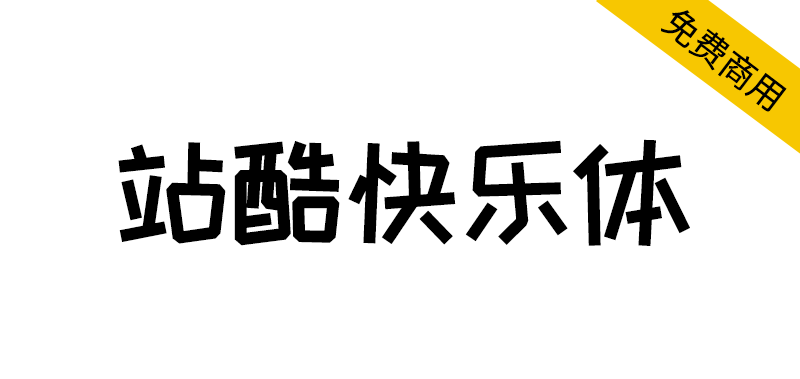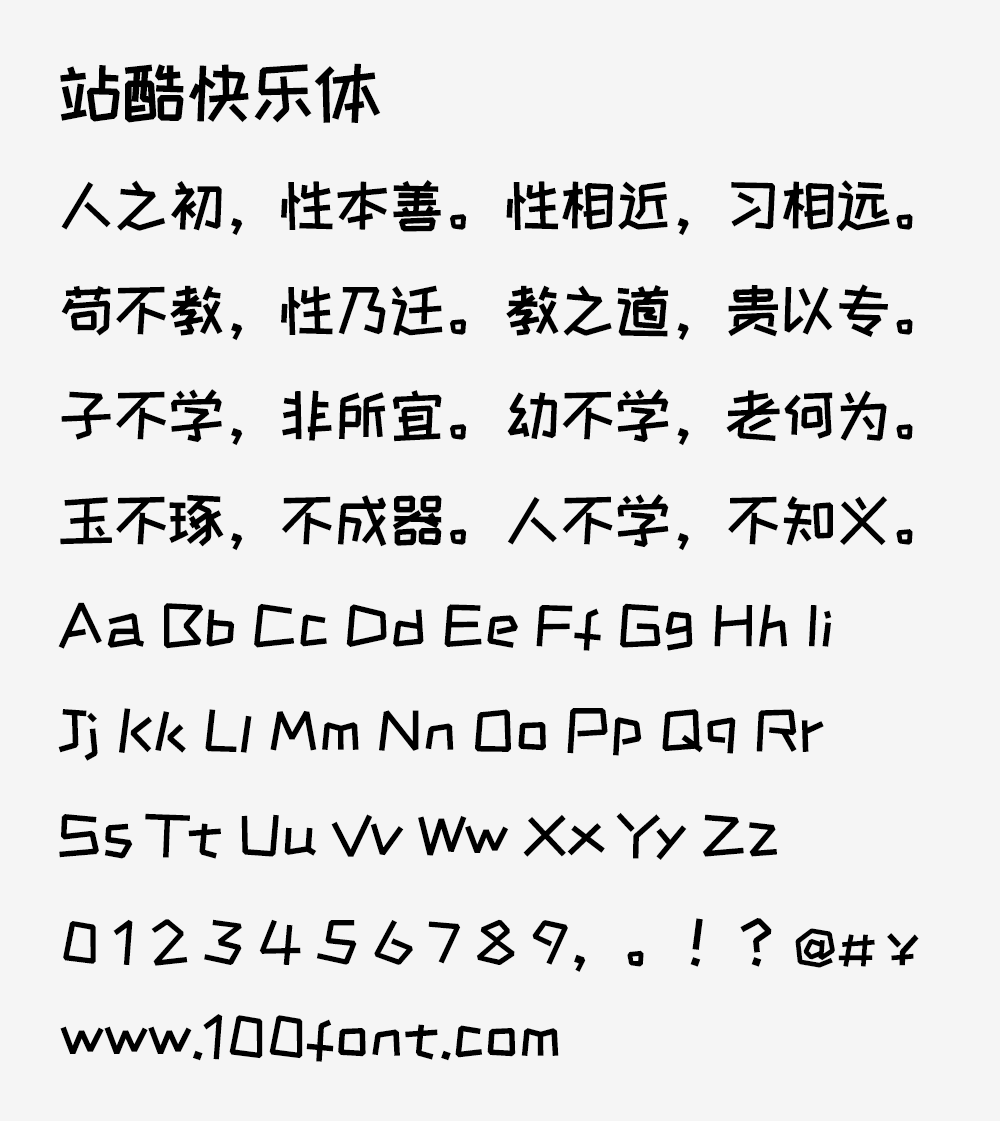
「站酷快乐体」是由字体设计师刘兵克组织其字体设计学员进行的字体设计活动,由刘兵克提供字形框架和设计规范,由100多位学员朋友按照各自字体内容设计出基本字形,然后再由刘兵克字体设计工作室成员杨康和吴少杰进行设计修改和调整完成。发布于2015年9月。
「站酷快乐体2016修订版」,是在“站酷快乐体”基础上进行的大幅修改与提升,本次修订工作的设计前期,由刘兵克学员团队和工作室团队共同完成,设计后期,由刘兵克进行了逐一修改与调整,经过多轮校审之后,于2016年6月正式对外公布和提供下载,整个工作耗时7个月。
站酷快乐体于2018年11月20日上传至谷歌字体,并以SIL Open Font License 1.1授权释出。2021年5月13日,站酷设计师@skr_ZERO子发布站酷快乐体部分汉字字形问题依旧存在,于是便进行了修正并发布了新的版本。
关于站酷字体:站酷公益字体,源自2014年的一次公益造字活动。由站酷ZCOOL的活跃字体设计师胡晓波及刘兵克发起这个项目,并设计最初的字形规范及基本部首,其余字形以众包的形式由分散在全国的79名设计师分别完成,最终一套好用并且免费的中文字体“站酷高端黑”诞生并在2014年圣诞发布。自从站酷高端黑之后,有更多的设计师团队和个人将字体赠送给站酷公益字体项目,交由站酷传播,给更多设计师使用。
一套标准的中文字库包含6000多个汉字,制作中文字体是一件非常困难的事情,现有的中文字体也远远满足不了设计师们的需求。因而站酷公益字体受到很多设计师的欢迎。
站酷快乐体采用GB2312汉字编码,共收录6763个汉字。很显然,站酷快乐体,是一枚可爱有趣、活泼俏皮的个性字体,可以根据字体的形式特点,应用在动漫、电视剧、零食包装等环境中。